Instagram 글꼴을 사용자 정의하는 방법?
운 좋게도 맞춤형 Instagram 글꼴은 포함되지 않습니다.
유명인과 인플루언서가 Instagram 계정에서 사용하는 멋진 글꼴 뒤에는 여러분이 알 수 없는 비밀이 없습니다. 멋진 글꼴을 얻으려면 Instagram 글꼴 생성 도구를 사용해야 합니다.
Instagram은 Instagram 스토리를 사용자 정의할 수 있는 5가지 글꼴을 제공하지만 약력, 캡션 및 댓글의 경우 Instagram은 하나의 옵션만 제공합니다. 따라서 Instagram Stories용 Instagram 프로필에서 멋진 글꼴을 얻으려면 계속 읽으십시오.
멋진 글꼴과 멋진 텍스트를 얻기 위해 Instagram 글꼴을 사용자 지정하는 방법을 시작해 보겠습니다.
Instagram 글꼴을 사용자 정의하는 방법은 무엇입니까?
Instagram 댓글, 약력, 캡션의 글꼴을 변형하고 싶거나 Instagram 스토리를 사용자 정의하고 싶거나 우리가 다룹니다.
Instagram은 많은 옵션을 제공하지 않기 때문에 서드파티 앱이나 도구를 사용하여 글꼴을 변경하게 됩니다.
버킷리스트에서 선택하는 도구는 사람마다 다릅니다. 모든 도구는 Instagram에서 사용할 멋진 텍스트를 제공합니다.
Instagram 프로필, 댓글, 약력 또는 Instagram 스토리에 텍스트를 사용하는 것이 확실하면 Instagram에 복사하여 붙여넣고 이름, 약력, 캡션 또는 댓글을 업데이트하세요.
Instagram 글꼴을 변경하는 최고의 온라인 도구 및 앱
1. LingoJam: 이것은 웹 기반 최고의 Instagram 글꼴 생성기 도구로, Instagram 스토리, 게시물, 댓글 또는 약력에 대한 멋진 텍스트를 얻는 데 사용할 수 있습니다. 도구를 사용하려면 왼쪽 섹션에 텍스트를 입력하고 오른쪽에 멋진 텍스트를 가져옵니다.
텍스트를 복사하여 Instagram에 붙여넣습니다. 이 멋진 텍스트, 멋진 글꼴은 Instagram 스토리, Instagram 프로필, 댓글 섹션을 매력적으로 만드는 데 사용할 수 있습니다.
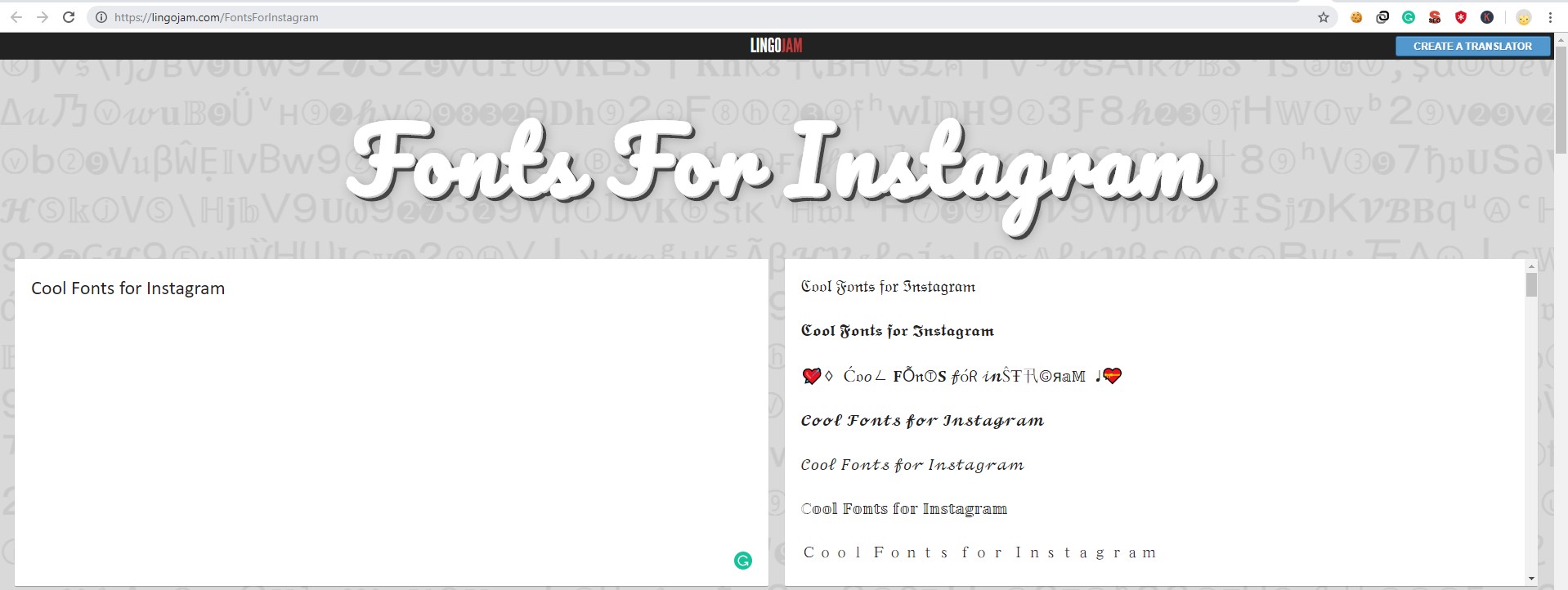
LingoJam은 간단한 텍스트를 멋진 텍스트로 변경할 수 있는 수많은 옵션을 제공합니다. 이 모든 옵션은 오른쪽에 있습니다. 일부는 전통적이고 일부는 창의적일 것입니다.
2. 인스타그램 글꼴: 이것은 Instagram을 위한 또 다른 최고의 온라인 글꼴 생성 도구입니다. Instagram 글꼴을 사용하면 Instagram을 위한 멋진 글꼴을 얻을 수 있으며 이 도구는 LingoJam처럼 작동합니다.
상자에 텍스트를 입력하기만 하면 그 아래 창에서 멋진 텍스트와 멋진 글꼴을 얻을 수 있습니다.
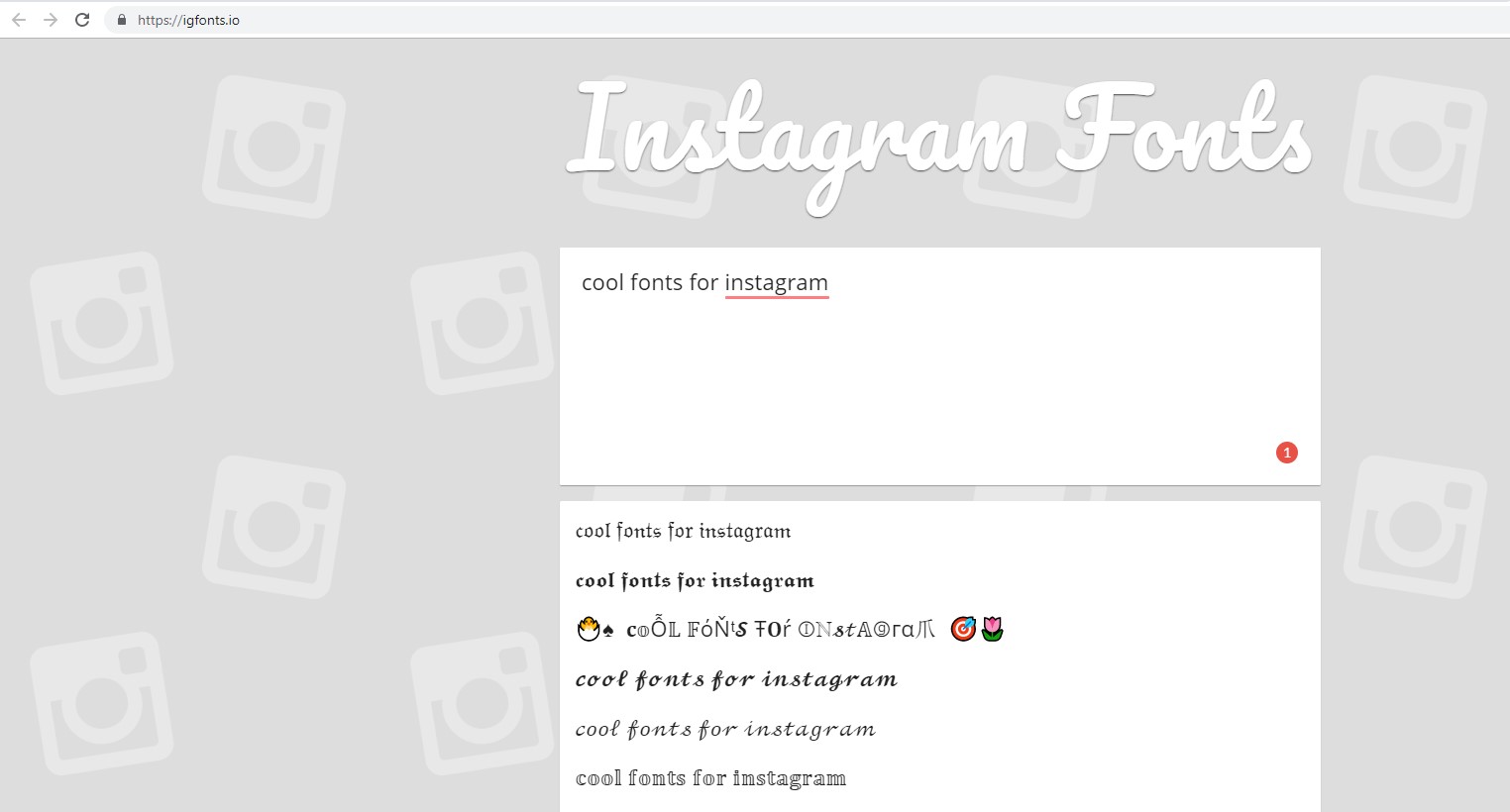
참고: Instagram용 웹 기반 글꼴 생성 도구의 유일한 문제는 휴대 전화에서 사용하는 동안 사용하기 쉽다는 것입니다. 따라서 모바일 앱을 사용하는 것이 훨씬 쉽고 간편하므로 더 나은 생각입니다.
이 앱을 사용하려면 iPhone 사용자가 먼저 글꼴을 선택한 다음 텍스트를 입력해야 합니다. 이렇게 하면 Instagram에 사용할 수 있는 멋진 글꼴로 멋진 텍스트를 만드는 데 도움이 됩니다. 이뿐만 아니라 이모티콘도 추가할 수 있습니다.
모바일 앱과 웹사이트를 사용하는 것의 장점은 앱이 사용하기 쉽고 부피가 적다는 것입니다. 또한 웹 사이트와 모바일 앱을 사용하여 사용자 정의 키보드도 사용할 수 있습니다.
4. 스프레즈 : 이것은 아마도 iPhone 사용자에게 가장 쉬운 방법일 것입니다. 이 iPhone을 사용하면 Instagram 글꼴을 멋진 텍스트로 사용자 지정할 수 있습니다. Sprezz는 Instagram 스토리, 댓글, 약력 등에 멋진 글꼴을 추가하는 데 사용할 수 있는 맞춤형 키보드입니다. 그러나 Sprezz는 제한된 옵션을 제공한다는 단점이 있습니다.
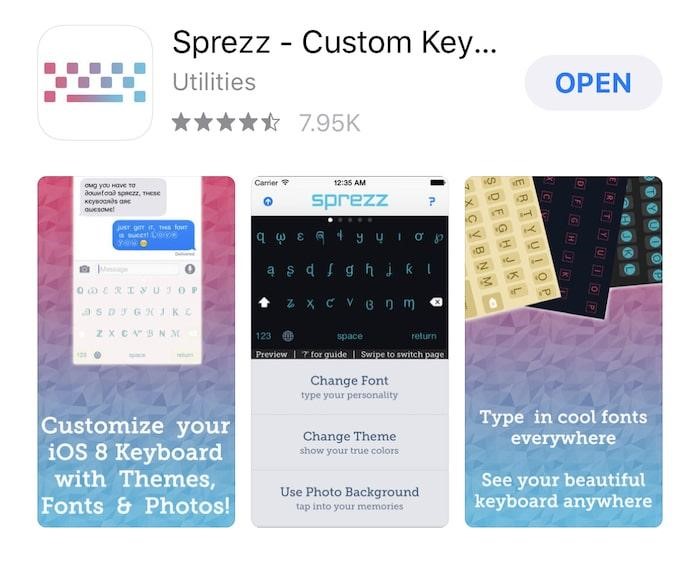
당신이 안드로이드 사용자라면 당신을 위한 것이 아무것도 없다고 생각해야 합니다. Adobe Spark Post는 Android 및 iPhone 사용자 모두에게 작동하는 앱입니다.
5. Adobe Spark Post: 소셜 미디어 이미지를 강화하고 멋진 텍스트, 멋진 글꼴을 추가하고 싶을 때 Adobe Spark Post는 Android 및 iPhone 사용자 모두가 사용할 수 있는 앱입니다.
멋진 텍스트를 추가하고 이미지를 멋지게 보이게 하는 등 다양한 기능을 제공합니다. 앱을 사용하려면 사진을 추가하거나 게시물을 열기만 하면 됩니다. 완료되면 글꼴 옵션을 눌러 다른 글꼴 스타일을 찾아 글꼴을 변경합니다.
원하는 글꼴을 선택하고 미리 볼 수 있습니다. 또한 모양, 효과 등으로 조정할 수 있습니다.
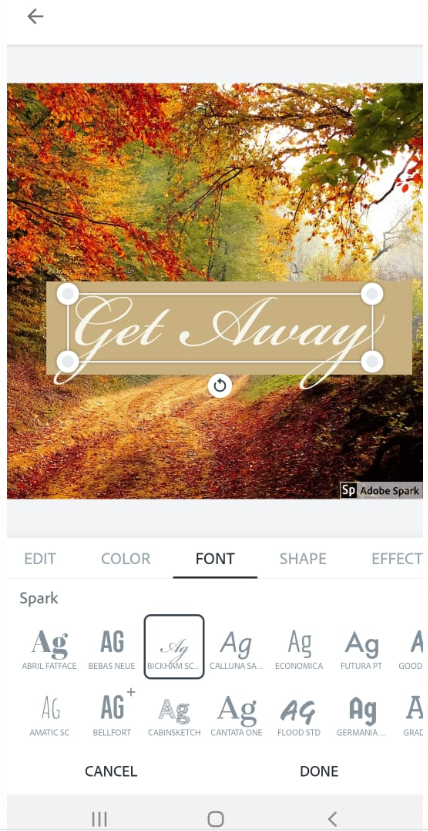
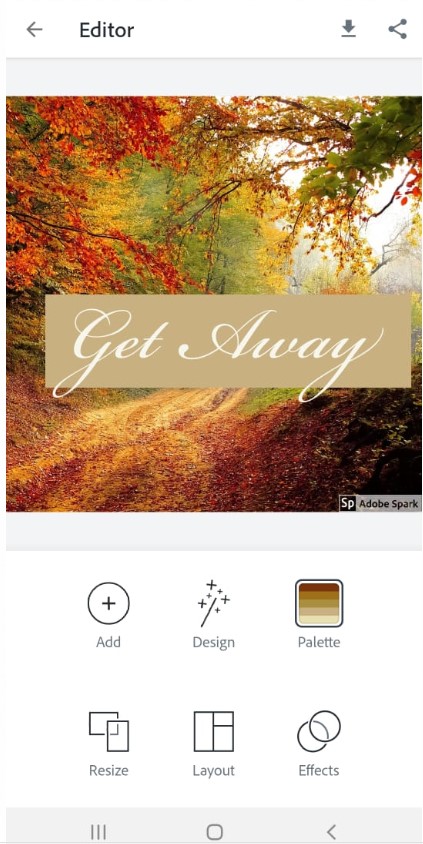
템플릿이 준비되면 저장하고 Instagram 스토리나 게시물에 이미지를 추가하세요.
이 외에도 Instagram Bio의 텍스트에 기호를 추가하려면 CoolSymbol.com 으로 이동하여 기호를 선택하고 복사하여 Instagram에 붙여넣습니다.
Instagram 앱을 사용하여 Instagram Stories 글꼴을 변경하는 방법은 무엇입니까?
타사 앱을 사용하여 글꼴을 변경하고 싶지 않은 경우 Instagram Stories에서 제공하는 옵션을 사용할 수 있습니다. 사용 방법은 다음과 같습니다.
- 인스타그램 계정 열기 > 스토리 만들기.
- 텍스트 전용 스토리를 만들려면 유형 옵션을 탭하세요.
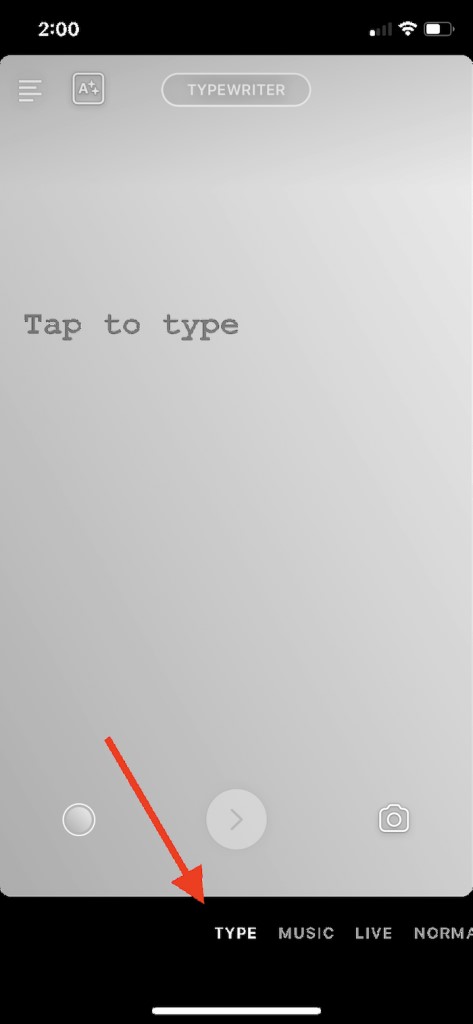
- 그런 다음 글꼴 표시기를 눌러 다른 옵션을 확인하십시오. 원하는 경우 텍스트를 먼저 추가할 수 있습니다.
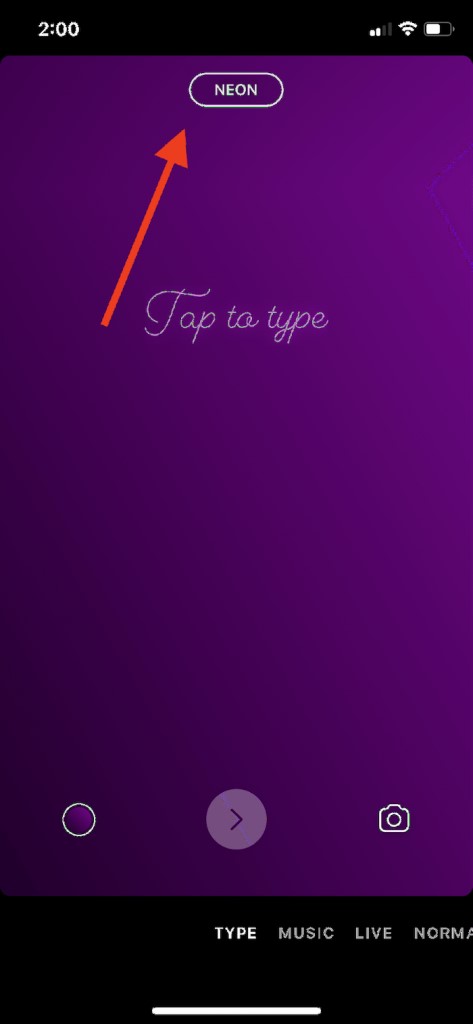
- 글꼴이 선택되면 오른쪽 화살표를 클릭하여 더 많은 색상 옵션을 가져옵니다. 원하는 색상을 선택하면 끝입니다.
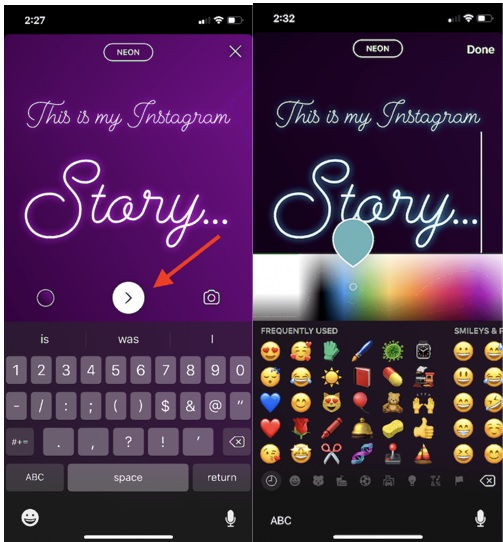
Instagram에서 멋진 텍스트와 멋진 글꼴을 사용할 때 명심해야 할 팁:
멋진 글꼴과 멋진 텍스트가 매력적이지만 Instagram 프로필에 멋진 텍스트를 추가하는 동안 스토리에 특정 사항을 염두에 두어야 합니다.
1) 일정하게 유지
이동 중에 많은 콘텐츠를 만들고 있지만 완벽한 스토리를 만들 시간이 없다면 한 가지 글꼴 유형을 사용하세요. 스토리의 아름다움은 콘텐츠의 획일성과 가독성에 있습니다.
2) 읽기 쉬운 글꼴 선택
Instagram 프로필이나 스토리에 어떤 멋진 글꼴을 사용하든 상관 없습니다. 사용자의 관심을 끌 유일한 것은 멋진 글꼴의 가독성입니다.
3) 다른 인스타그램 글꼴 사용 피하기
다른 글꼴을 사용하면 가독성이 떨어지므로 멋진 글꼴을 현명하게 선택하십시오.
텍스트가 평범한 단어보다 더 많이 말하게하십시오.
Instagram은 시각적 중심 플랫폼이므로 Instagram 프로필을 사용자 지정하기 위해 멋진 글꼴을 사용하여 게시물을 눈에 띄게 만들고 흥미롭게 만드는 것은 멋진 아이디어입니다. 이를 위해서는 올바른 도구를 사용하고 Instagram 바이오를 흥미롭게 만들어야 합니다.